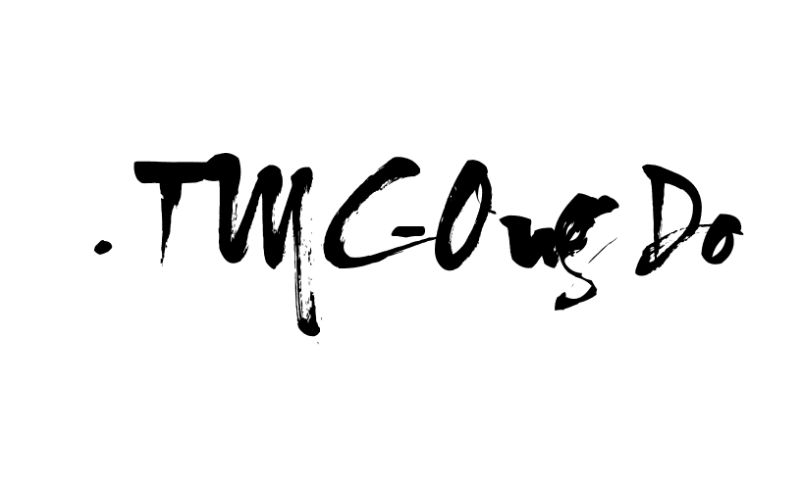
Nếu bạn đang tìm kiếm những kiểu chữ mang đậm nét nghệ thuật Á Đông cho thiết kế của mình, thì tải font thư pháp Việt hóa chính là lựa chọn hoàn hảo. Font thư pháp giúp bạn thể hiện tinh thần truyền thống, sự mềm mại và cảm xúc trong từng nét chữ — từ thiệp chúc Tết, poster, thư mời cho đến thiết kế thương hiệu. Trong bài viết này, hãy cùng Vietkey khám phá các font thư pháp Việt hóa đẹp, dễ dùng và hoàn toàn miễn phí, giúp bạn sáng tạo nội dung độc đáo, mang đậm dấu ấn văn hóa Việt.
Giới thiệu về font thư pháp việt hóa
Font thư pháp Việt hóa là những kiểu chữ được chuyển thể từ các mẫu thư pháp truyền thống và được bổ sung bộ ký tự tiếng Việt đầy đủ, giúp người dùng dễ dàng sử dụng trong thiết kế. Khác với các font thông thường, font thư pháp mang đường nét uốn lượn, mềm mại và giàu cảm xúc, thể hiện tinh thần nghệ thuật và bản sắc Á Đông. Nhờ được Việt hóa, các font này hỗ trợ tốt dấu tiếng Việt, đảm bảo tính thẩm mỹ trong các ấn phẩm như thiệp chúc Tết, poster, thư pháp số hay thiết kế logo mang phong cách cổ điển, sang trọng. Đây là lựa chọn lý tưởng cho những ai muốn kết hợp giữa truyền thống và hiện đại trong các dự án sáng tạo.
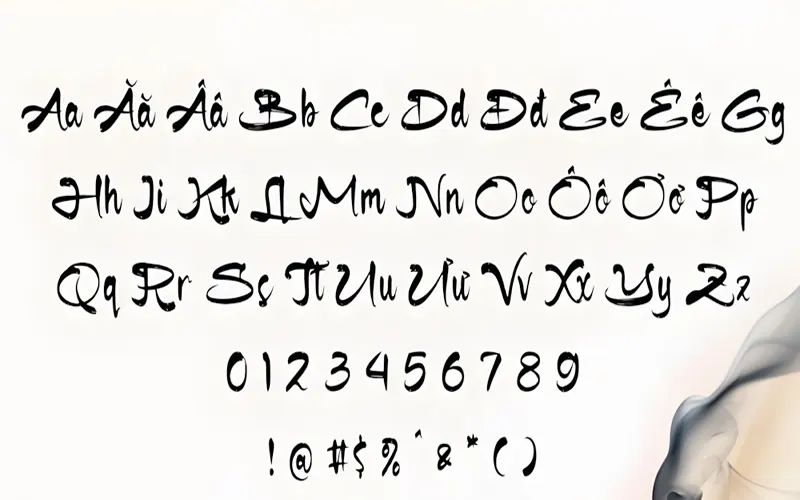
Vì sao nên chọn font thư pháp Việt hóa thay vì font thường?
Việc sử dụng font thư pháp Việt hóa mang lại nhiều ưu điểm vượt trội so với các font chữ thông thường. Trước hết, chúng giúp truyền tải cảm xúc và tinh thần nghệ thuật rõ nét hơn nhờ đường nét uyển chuyển, mềm mại và mang đậm hơi thở Á Đông. Thứ hai, các font đã được Việt hóa hoàn chỉnh nên hiển thị đầy đủ dấu tiếng Việt, tránh lỗi font hoặc mất ký tự khi thiết kế.
Ngoài ra, font thư pháp Việt hóa còn giúp tác phẩm trở nên độc đáo, khác biệt và có chiều sâu văn hóa – điều mà các font hiện đại phổ thông khó thể hiện được. Dù bạn thiết kế thiệp mừng, poster nghệ thuật hay dự án sáng tạo cá nhân, việc chọn font thư pháp Việt hóa sẽ giúp tăng tính thẩm mỹ và tạo dấu ấn riêng cho sản phẩm của bạn.
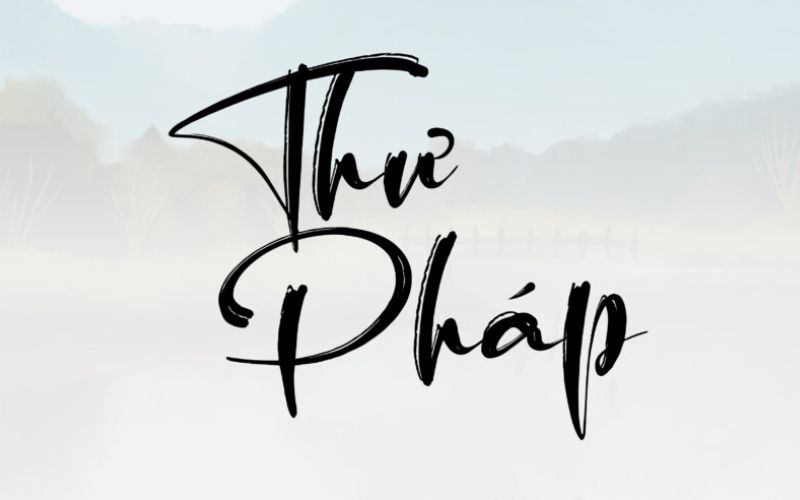
Các font thư pháp Việt hóa đẹp và được tải nhiều nhất hiện nay
Hiện nay, font thư pháp Việt hóa đang được nhiều designer và người yêu nghệ thuật lựa chọn nhờ khả năng thể hiện cảm xúc tinh tế và hỗ trợ tiếng Việt đầy đủ. Dưới đây là tổng hợp những font thư pháp Việt hóa đẹp, dễ dùng và được tải nhiều nhất mà bạn nên thử:
Font DL Thu Pháp và Font Thư Pháp Thành Công – Tết
Hai font này nổi bật với nét chữ mềm mại, uyển chuyển, thể hiện rõ tinh thần truyền thống Việt Nam. Chúng đặc biệt phù hợp cho các thiết kế thiệp Tết, banner quảng cáo hoặc thư pháp số. Nhờ sự thanh thoát và tinh tế, DL Thu Pháp và Thư Pháp Thành Công – Tết mang lại cảm giác gần gũi, đầy cảm xúc trong từng nét chữ.
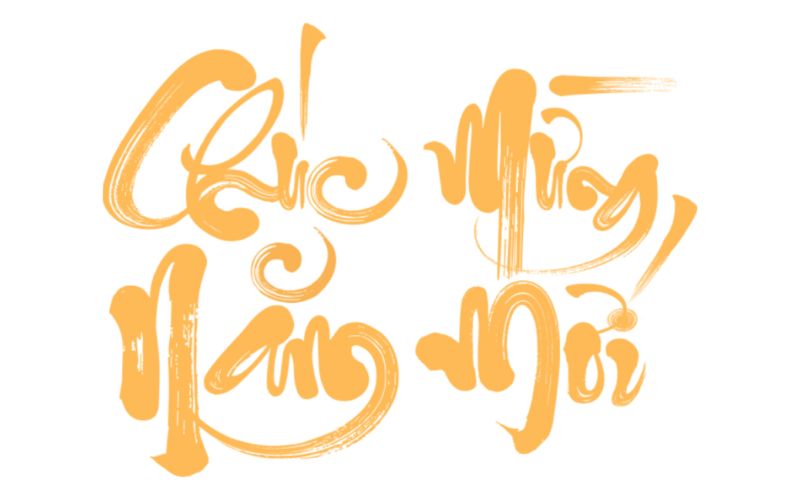
Font VNI Thu Pháp Việt Hóa và UVN Thư Pháp
Đây là nhóm font thư pháp Việt hóa mang phong cách cổ điển và sang trọng. Với đường nét mạnh mẽ, uốn lượn tự nhiên, hai bộ font này thường được sử dụng trong thiết kế logo, ấn phẩm văn hóa, bìa sách hoặc tranh thư pháp kỹ thuật số. VNI Thu Pháp và UVN Thư Pháp giúp tạo điểm nhấn đậm chất nghệ thuật, phù hợp với các thiết kế mang yếu tố truyền thống.
Font VNI QUANG NINH
Font VNI QUANG NINH là một trong những font thư pháp Việt hóa nổi bật với thiết kế đơn giản, dễ đọc nhưng vẫn thể hiện được vẻ thanh lịch và tinh tế. Các nét chữ được tác giả chăm chút kỹ lưỡng, tạo nên sự cân bằng giữa độ đậm và nhạt, mang đến cảm giác mềm mại mà vẫn rõ ràng. Nhờ phong cách dung dị, gần gũi, font này thường được sử dụng trong thiết kế tiêu đề, slogan, bảng hiệu hoặc các ấn phẩm quảng bá văn hóa địa phương, giúp tác phẩm trở nên ấn tượng và mang đậm bản sắc truyền thống Việt Nam.
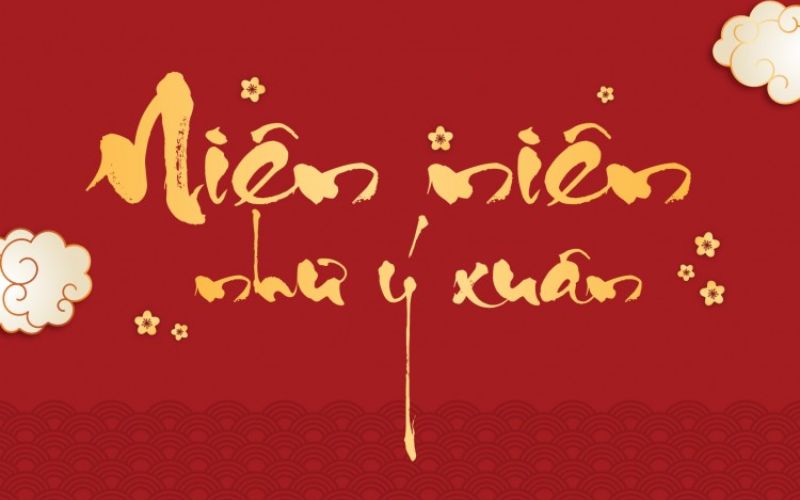
Font VNIThufapfan
VNIThufapfan là một trong những font thư pháp Việt hóa được yêu thích nhờ kiểu chữ rõ ràng, cân đối và dễ dàng kết hợp trong nhiều phong cách thiết kế khác nhau. Font mang lại cảm giác mềm mại nhưng vẫn giữ được sự chuyên nghiệp, giúp người dùng linh hoạt khi ứng dụng vào các dự án thiết kế đồ họa, poster, banner hoặc ấn phẩm quảng cáo. Nhờ tính ứng dụng cao và khả năng hiển thị tốt, VNIThufapfan trở thành lựa chọn phổ biến cho những ai muốn tạo điểm nhấn nghệ thuật trong thiết kế mà vẫn đảm bảo tính thẩm mỹ và dễ đọc.